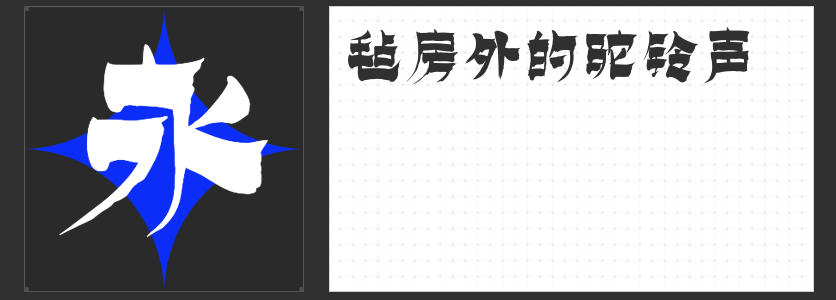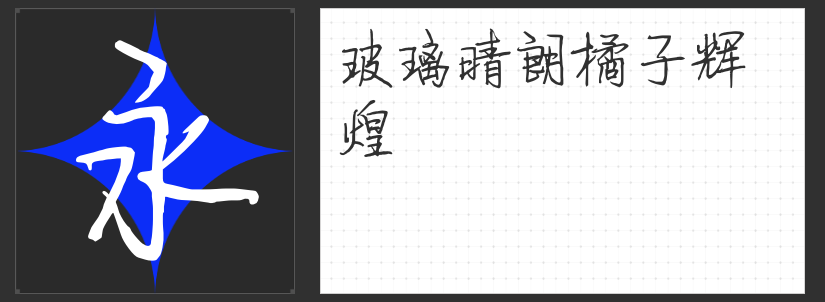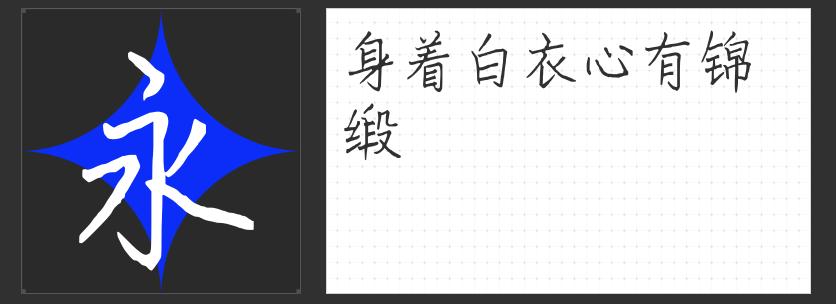
有创意且大气的书法字体,四款“云书法”字体推荐
在设计的世界里,字体不仅是信息的载体,更是情感与风格的传递者。今天,让我们一同探索“云书法”系列中的四款书法字体,它们不仅各具特色,更在设计中展现出无与伦比的魅力。
一、云书法玉兰行楷体
这款字体以其气韵生动、刚柔并济的特点,成为设计中的一大亮点。整体字形匀称,主笔画凸出,块面感明确,增强了视觉层次感。运笔自然流畅,笔画间牵丝连带,展现出毛笔书法的灵动与洒脱。无论是海报、文创产品,还是书籍封面、影视娱乐设计,云书法玉兰行楷体都能以其独特的韵味,为作品增添一抹不凡的艺术气息。
二、云书法永刚漆书体
这是一款极具创意的毛笔手书字体,笔画厚重而清晰,框架醒目,字型端庄,展现出一种从容不迫的灵性。其风格统一,适用于包装印刷、广告设计、平面设计等多个领域。云书法永刚漆书体的独特韵味,能够为作品赋予强烈的视觉冲击力,让人过目难忘。
这款字体,章法布白间气韵贯通,生动有趣。无论是灵动洒脱,还是端庄雅致的设计,这款字体都能在设计作品中展现出独特的魅力。它适用于各种需要展现文化底蕴与艺术品味的场合,如书籍装帧、品牌标识、展览展示等。
这款字作品如其作者,下笔稳如泰山,中锋书写有入木三分的力量而不失灵活轻盈,用墨浓淡适宜而又干净利落。其于章法布白,行文之中,气韵贯通,生动有趣,宽博雅致。
“云书法”系列字体,以其独特的艺术风格和广泛的应用场景,成为设计中的书法艺术瑰宝。它们不仅丰富了设计的语言,更让作品在传达信息的同时,传递出深厚的文化底蕴和艺术情感。选择“云书法”系列字体,让你的设计作品更加出彩,更加动人。